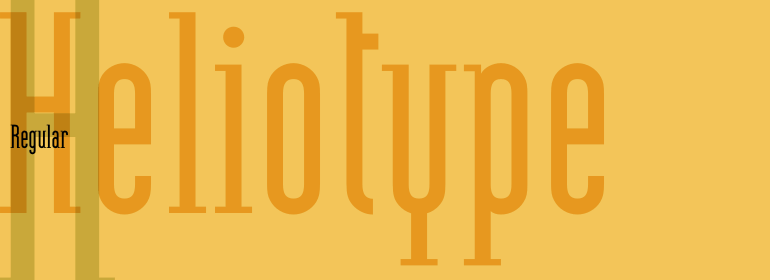
Heliotype™
Heliotype™,这款字体结构工整、笔画清晰,兼顾美观与易读性,适用于标题、正文、海报、包装、LOGO 等多种场景。字形优雅稳定,风格百搭耐看,适配日常排版与创意设计,让文字呈现更舒适、更具质感。Heliotype™一笔一画,皆是细节,以均衡的比例、流畅的线条打造舒适视觉体验,字形端正大气,风格简约现代。无论是商业设计、品牌宣传还是日常排版,都能轻松驾驭,让文字更有格调与力量。Heliotype™字体下载。